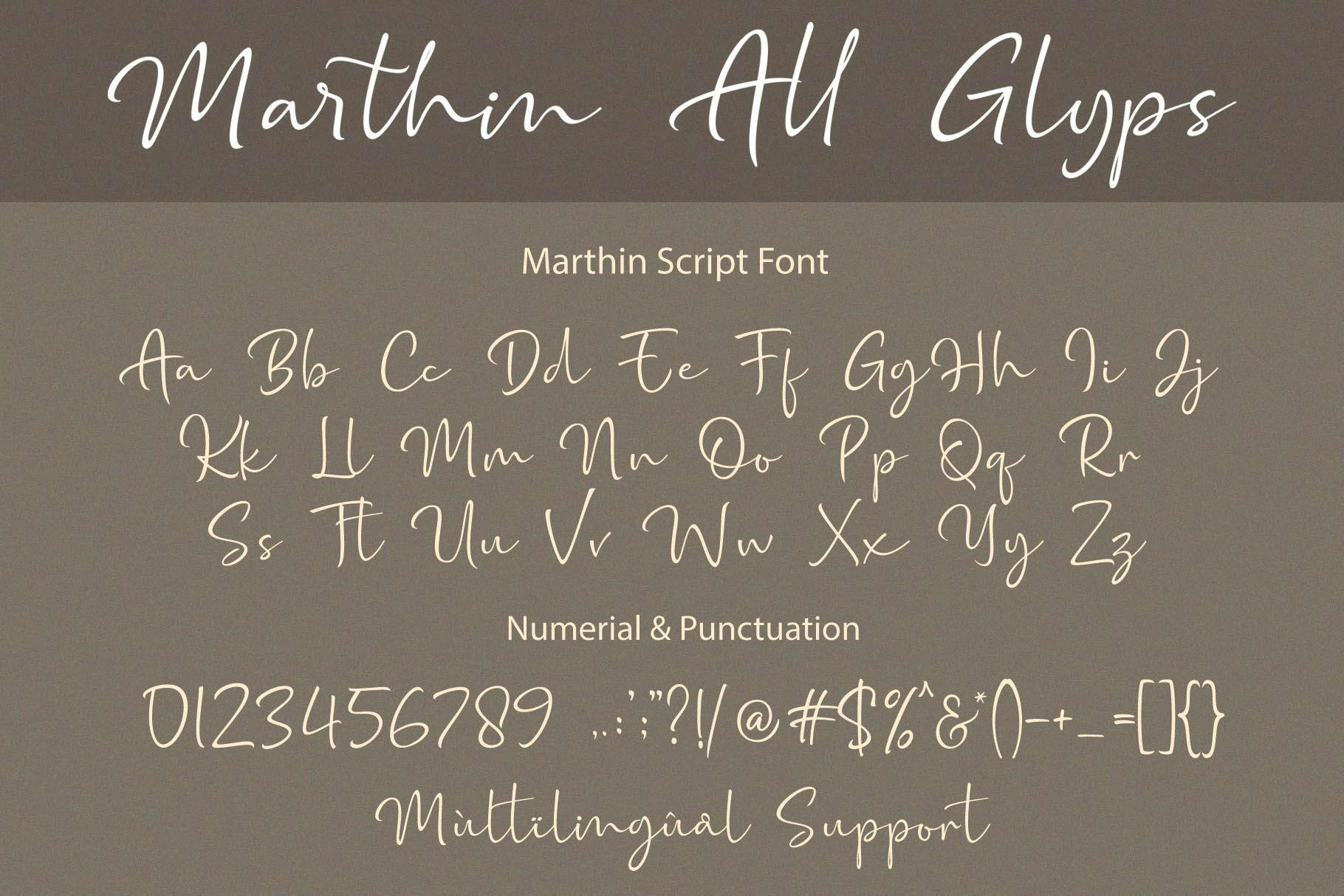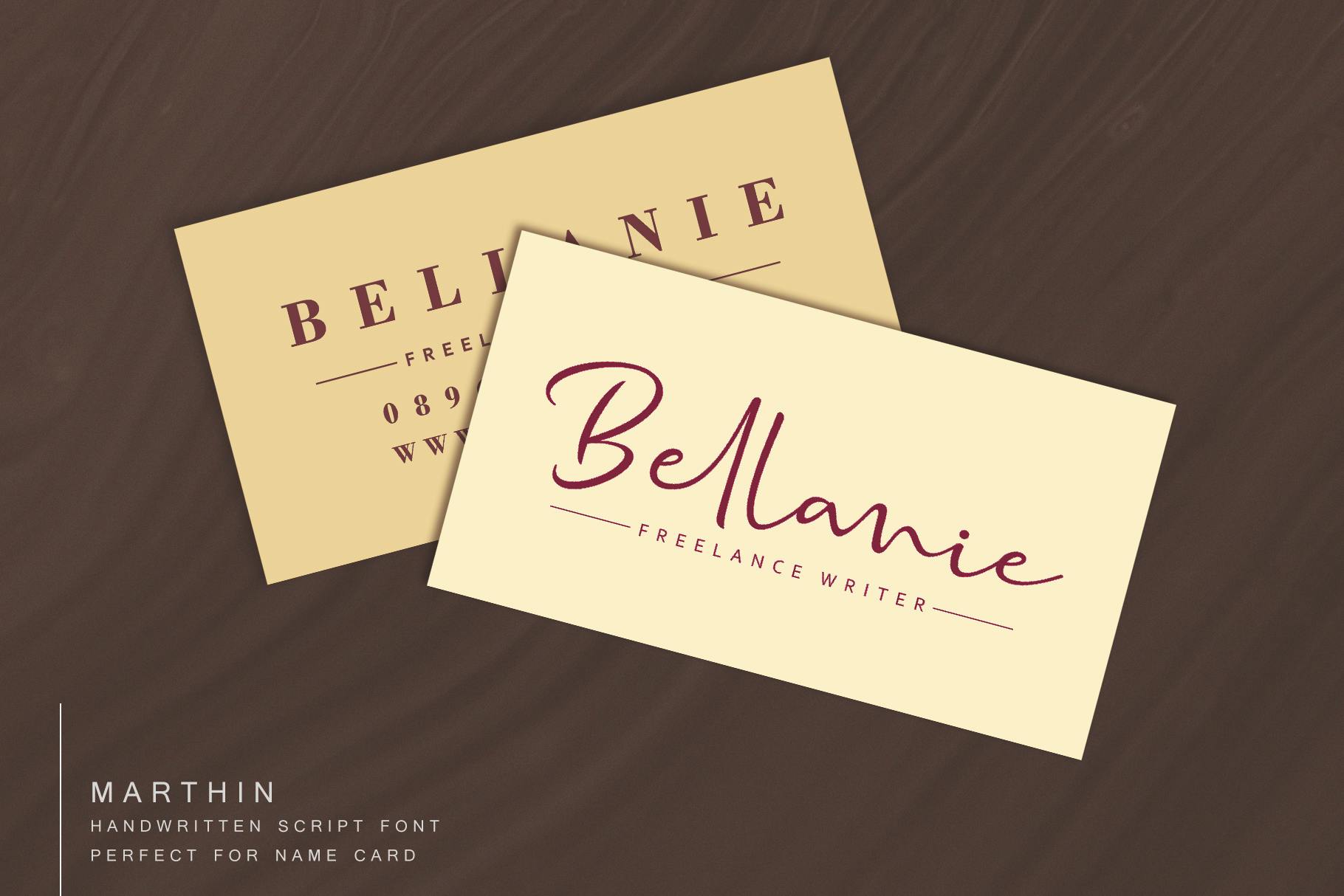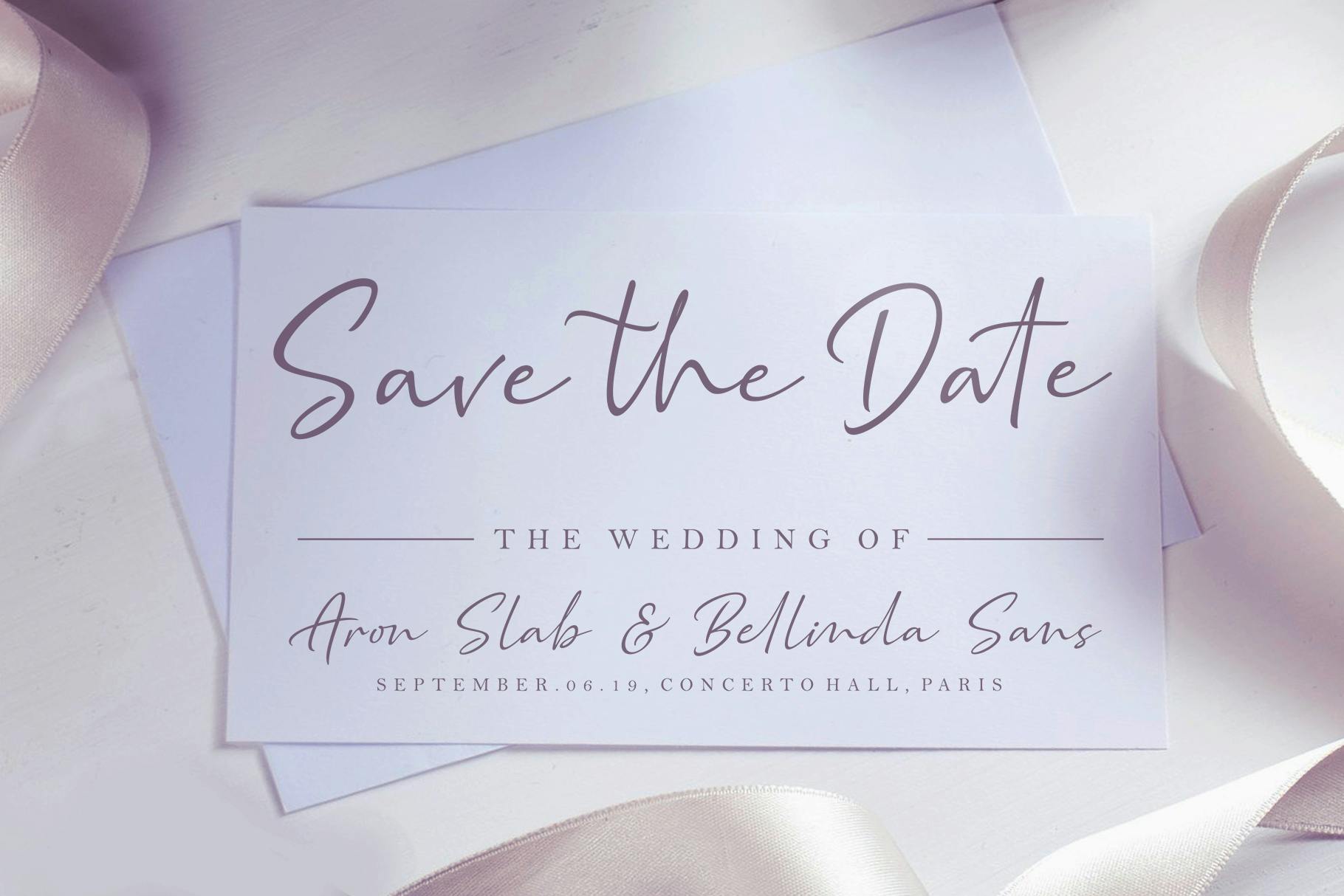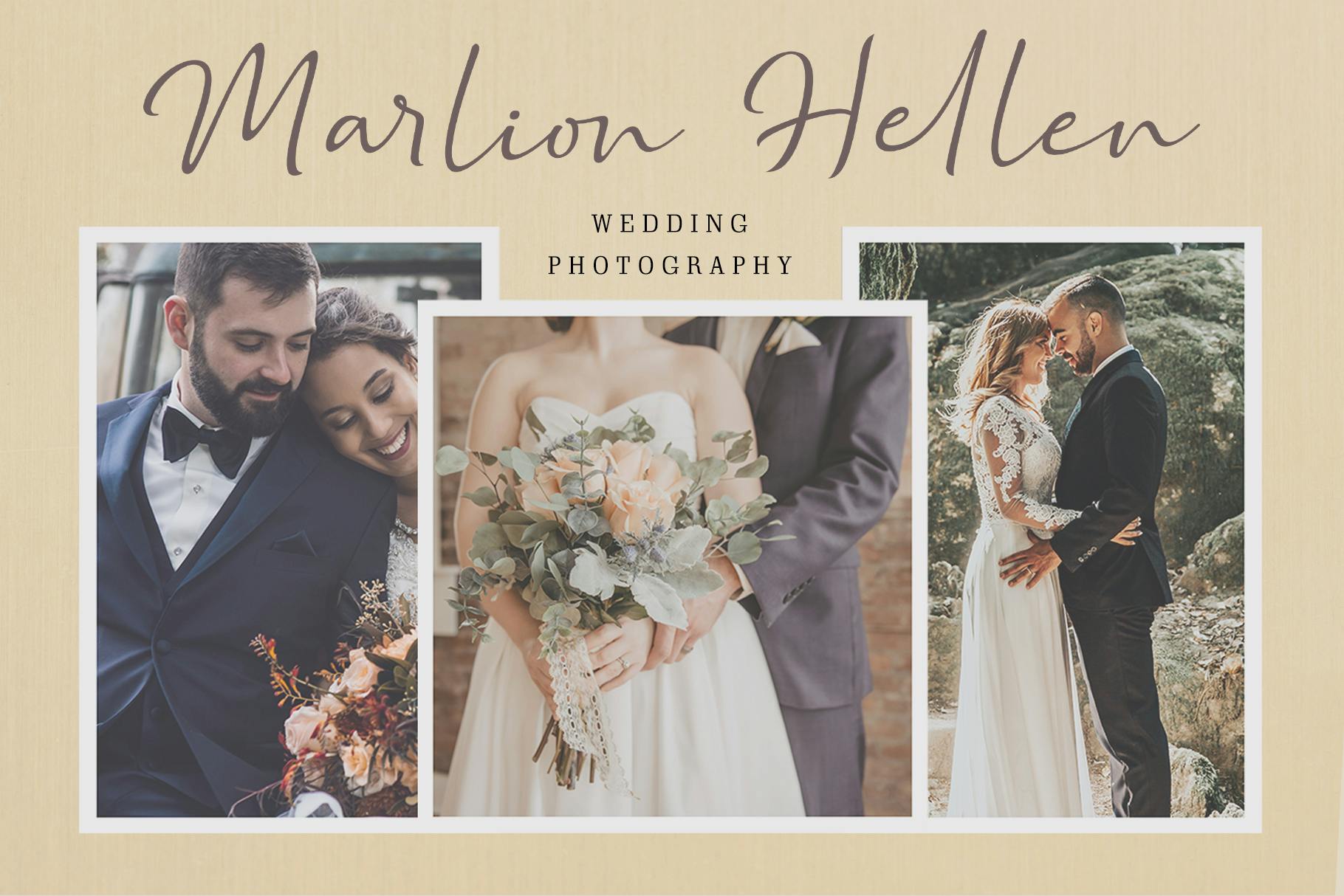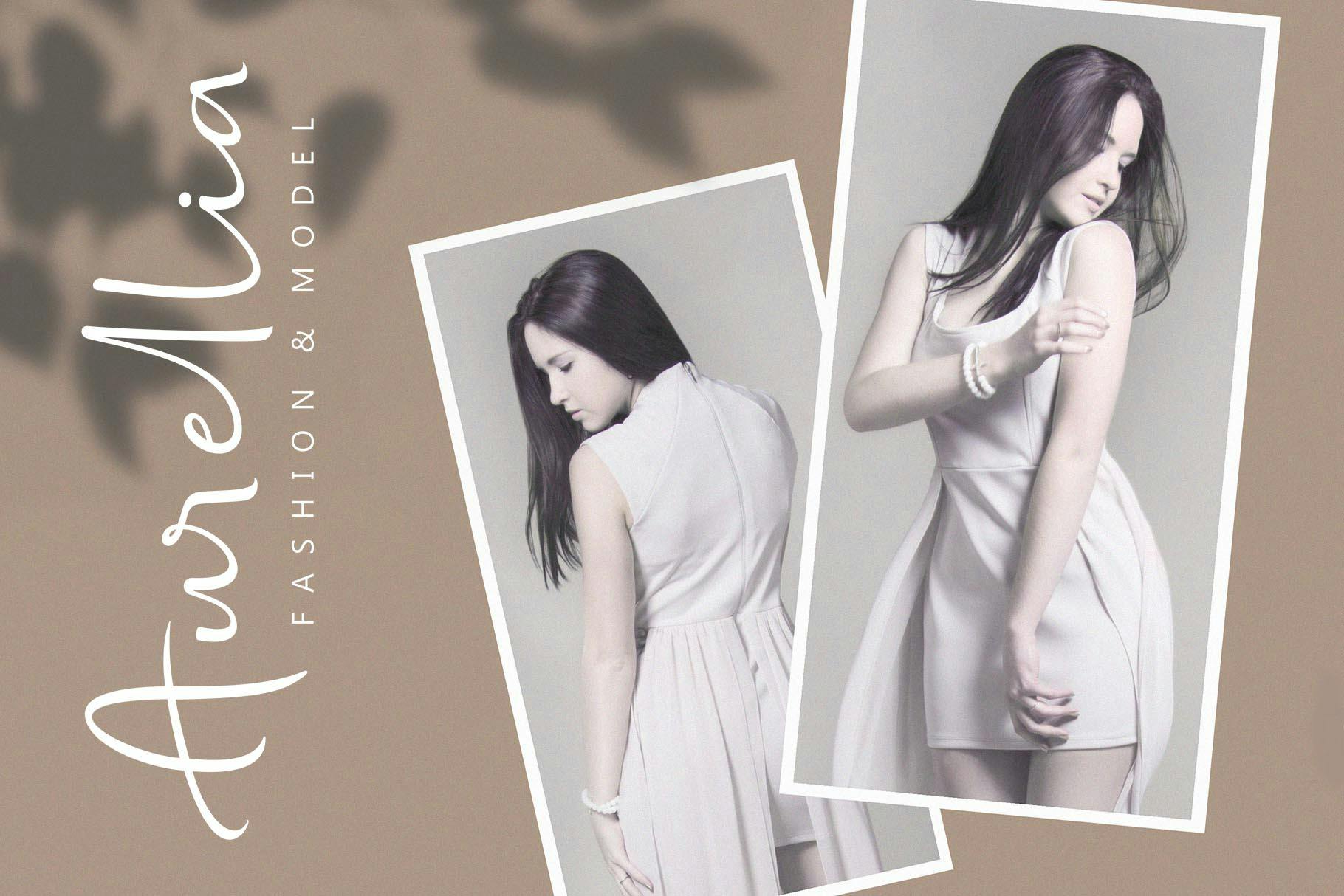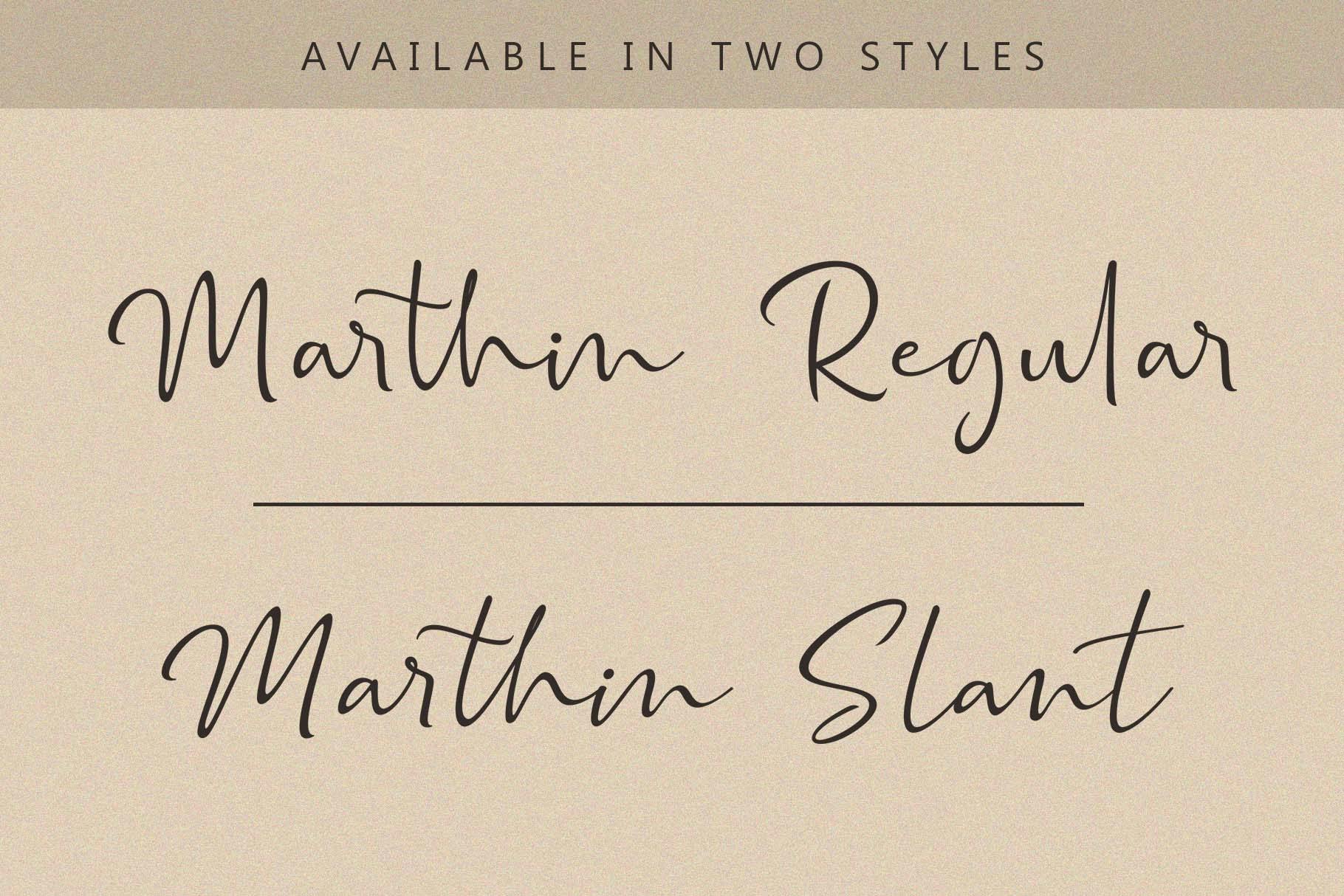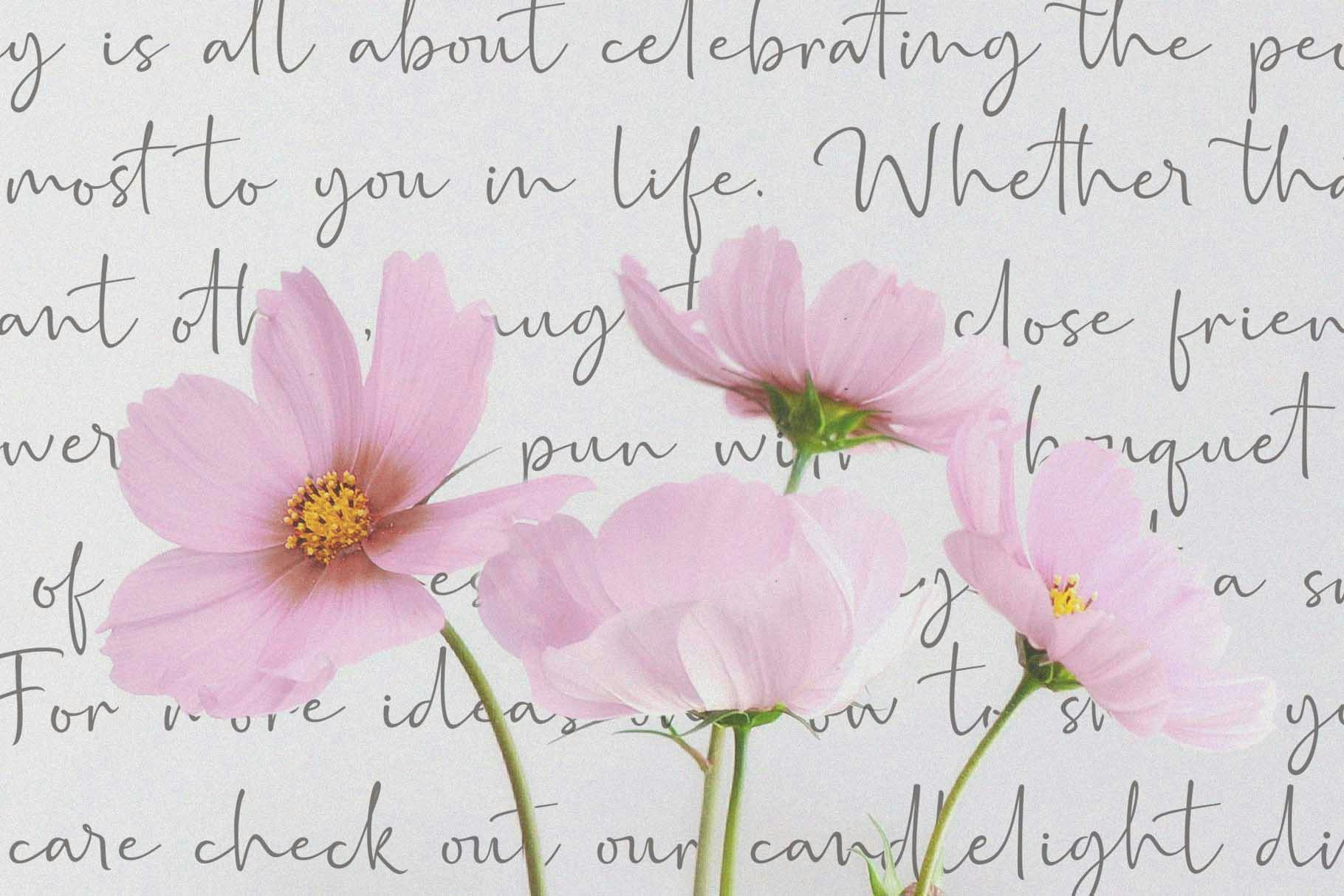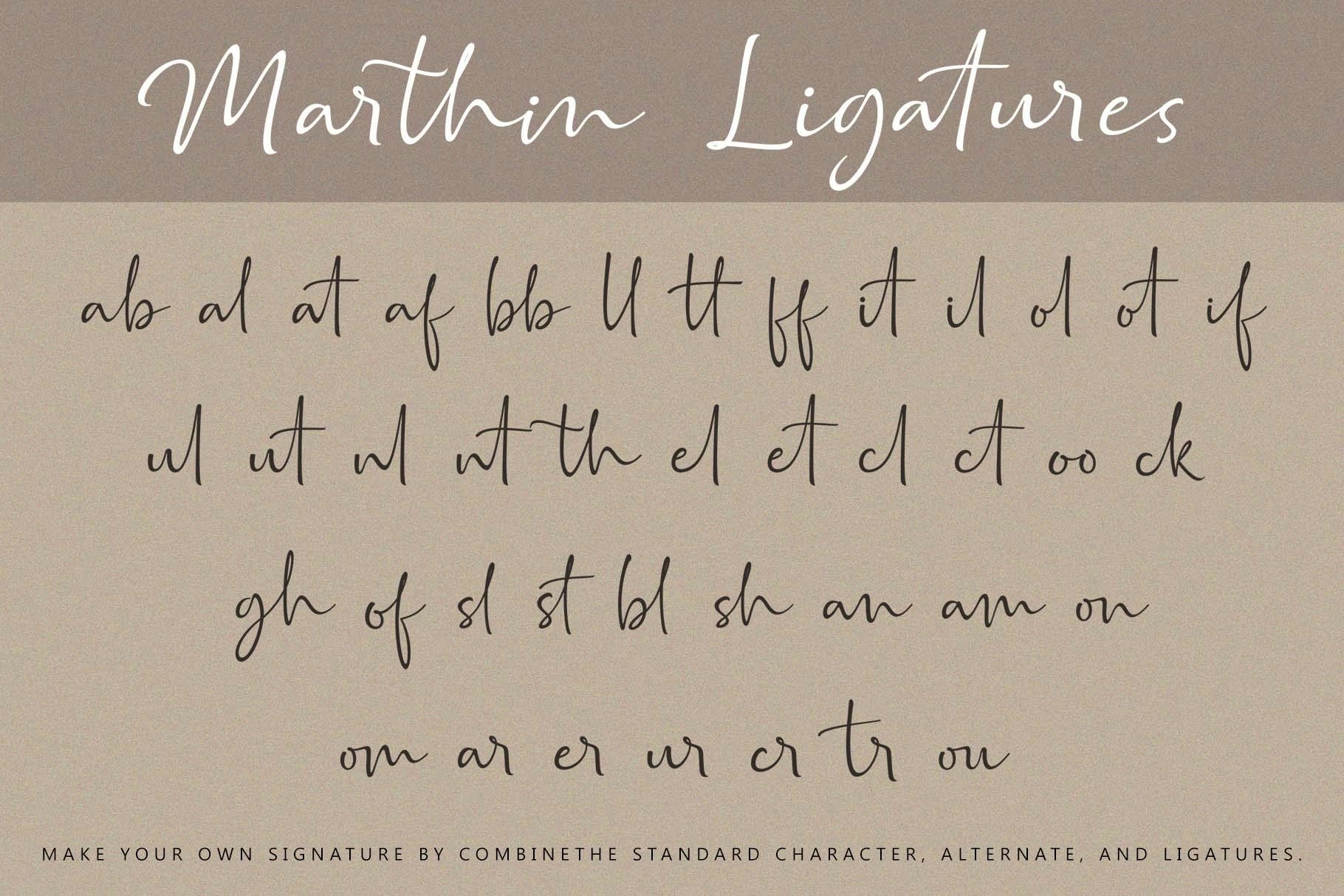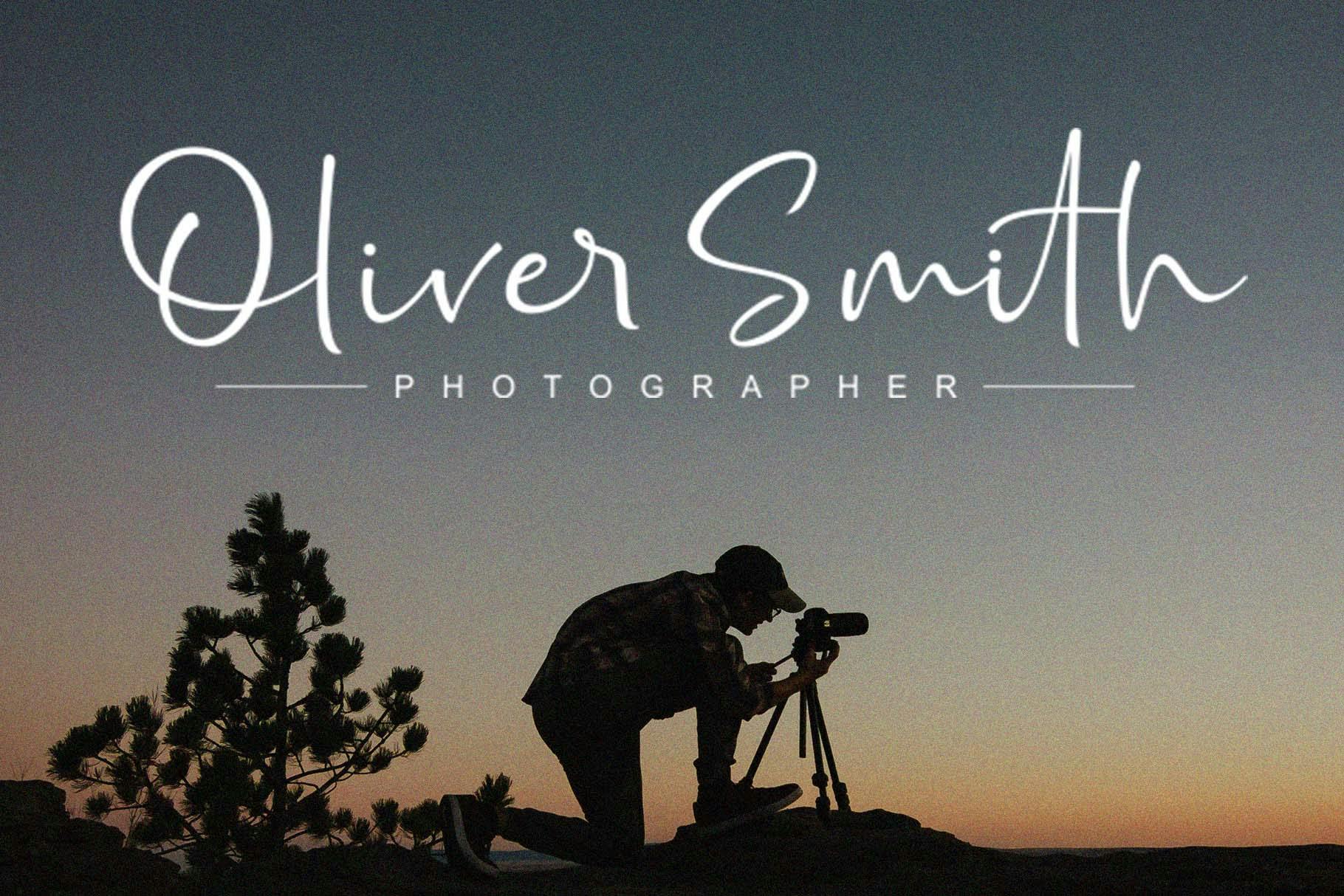
فونت مار تین را معرفی میکنیم - یک امضای مدرن جدید با خطوط زیبا که این فونت را برای برندینگ شخصی و هر پروژه فوقالعادهای ایدهآل میسازد. این فونت مناسب برای طراحی لوگوها، دعوتنامهها، لوازمالتحریر، طراحیهای عروسی، پستهای رسانههای اجتماعی، تبلیغات، بستهبندی محصولات، طراحی محصولات، برچسبها، عکاسی، واترمارکها، رویدادهای ویژه و بسیار بیشتر است!